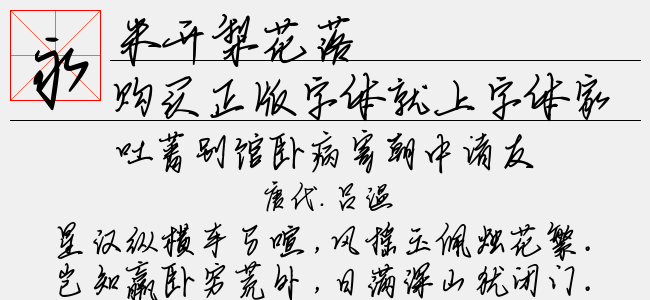
锐字工房云字库行草GBK.ttf
锐字工房云字库行草GBK.ttf是一款非常漂亮的艺术字体,锐字工房云字库行草GBK.ttf字体广泛用于各种书刊、画册的设计印刷中,锐字工房云字库行草GBK.ttf字体具有强烈的视觉冲击力,报纸和杂志和书籍中常用字体, 海报、个性促进品牌标志
锐字工房云字库行草GBK.ttf是一款非常漂亮的艺术字体,锐字工房云字库行草GBK.ttf字体广泛用于各种书刊、画册的设计印刷中,锐字工房云字库行草GBK.ttf字体具有强烈的视觉冲击力,报纸和杂志和书籍中常用字体, 海报、个性促进品牌标志设计、字体设计、等环境。 锐字工房云字库行草GBK.ttf字体是一款用于标题设计方面的字体,由字体下载站提供免费下载,字体下载大全提供最全最新的中、英文字体素材。